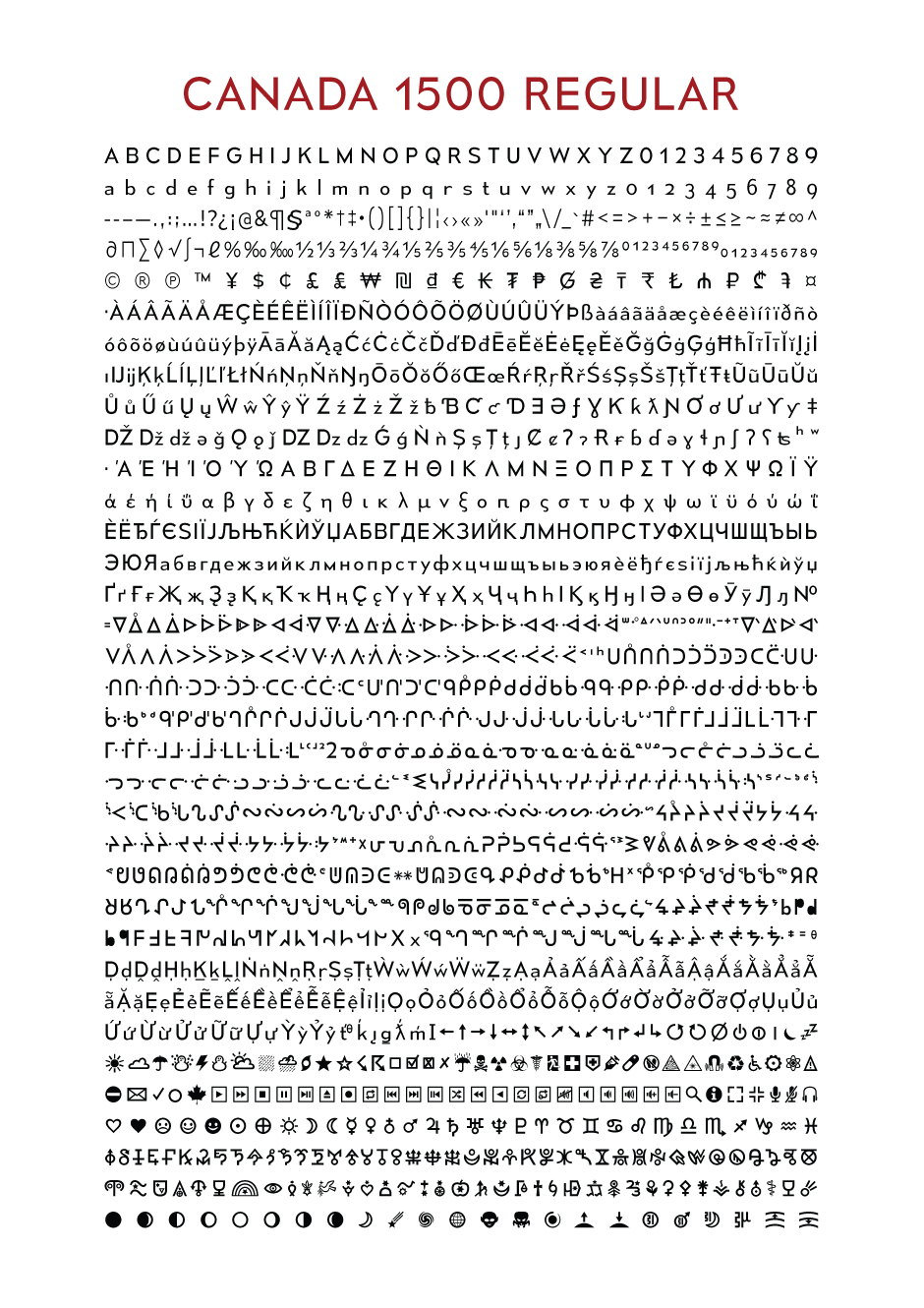
Canada 1500
Une police multilingue du domaine public créée pour le 150e anniversaire du Canada, puis adaptée à un projet de mission vers Mars.
Je suis Raymond Larabie, le créateur de Canada 1500. En novembre 2014, j’ai créé Mesmerize, une famille gratuite de quatre-vingts styles. En 2015, Grant Johnson, conseiller principal du Secrétariat fédéral Canada 150, m’a contacté pour adapter des styles de Mesmerize au logo du 150e anniversaire du Canada, célébré le 1er juillet 2017. J’ai proposé de créer gratuitement une famille personnalisée et j’ai étendu sa couverture aux langues autochtones du Canada.
La police Canada 150 était initialement distribuée par le Secrétariat fédéral Canada 150. En 2016, Constance Adams m’a contacté pour l’adapter à un projet de mission habitée vers Mars. J’ai nommé cette nouvelle version Canada 1500 et l’ai adaptée aux panneaux et aux étiquettes d’un vaisseau spatial et d’une base martienne. J’ai également ajouté le vietnamien, le grec, d’autres langues utilisant le cyrillique et la plupart des langues à alphabet latin en usage aujourd’hui.
Canada 1500 a été mise à jour pour mieux prendre en charge les langues autochtones et s’aligner sur des versions plus récentes d’Unicode. Cette mise à jour ajoute la lettre latine majuscule lambda, étend la couverture du carrier, du chipewyan et du nattilik, ajoute des caractères Extended-A, redessine plusieurs glyphes et transfère les sources originales de FontLab 5 vers FontLab 8.